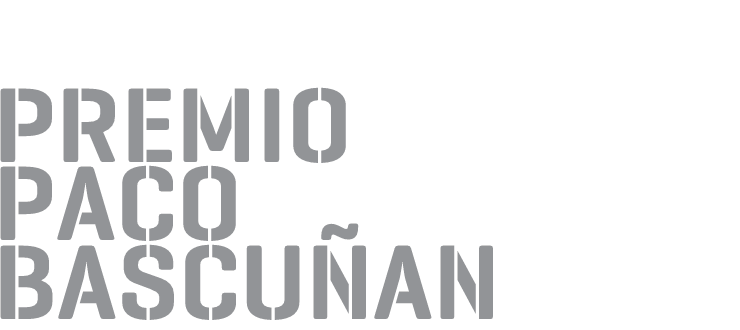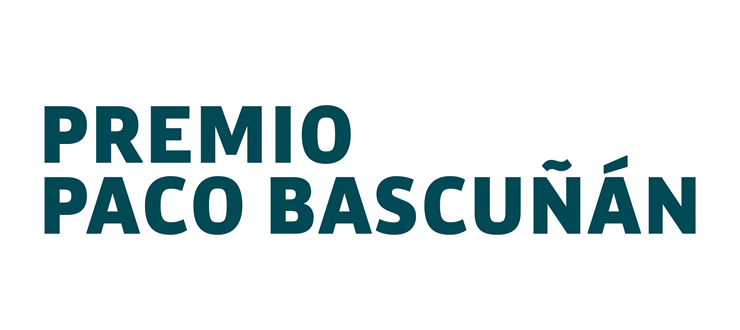
Premio de diseño de Tipografía “Paco Bascuñán”
Paco Bascuñán fue un diseñador socialmente comprometido y una de las figuras claves del diseño español desde la transición democrática hasta su muerte, acontecida prematuramente en 2009.
Convencido de que el diseño transmite valores y de que hay que otorgarle el lugar que le corresponde en la mejora de la sociedad, Bascuñán llevó también su compromiso a la mejora de la profesión.
Respetado por sus colegas de generación y admirado por los más jóvenes tanto por la calidad de su diseño como por su coherencia vital y su apertura de miras, Bascuñán fue y es un referente para quienes creen que el diseño es una profesión abierta y plural.
El Premio Paco Bascuñán es un homenaje a su figura pero, sobre todo, es la continuación de su labor en apoyo a los más jóvenes.
Bases de la convocatoria 2012
Presentación
El premio de tipografía Paco Bascuñán se plantea con dos objetivos principales: fomentar la tipografía y el diseño de tipos entre las nuevas generaciones y ser, a su vez, un homenaje a la figura de Paco Bascuñán, diseñador y tipógrafo, que siempre supo apoyar a los más jóvenes.
Bases de participación
La participación es gratuita. No podrán presentarse más de dos trabajos por autor. Podrán participar todos aquellos jóvenes menores de 25 años (cumplidos antes de Julio de 2012) con nacionalidad Española o residentes en territorio Español. Será necesaria la presentación de dicha documentación (copia de DNI o tarjeta de residencia) conjuntamente con los datos del autor.
Los trabajos presentados deberán haber sido realizados por su autor entre Enero de 2010 y Mayo de 2012.
Categorías
Se admiten alfabetos compuestos por glifos pertenecientes a cualquiera de los sistemas de escritura existentes conocidos.
1. Texto: alfabetos de estilo único o con múltiples variantes estilísticas diseñados básicamente para su uso en la composición de texto.
2. Display: alfabetos de estilo único o con múltiples variantes estilísticas diseñados para su uso a gran tamaño.
3. Ornamentales: conjuntos compuestos por glifos cuyo uso esté previsto para aplicaciones especiales: signos matemáticos, signos fonéticos, iconos, pictogramas, viñetas, ornamentos y todos aquellos casos no incluidos en las categorías anteriores.
Los alfabetos presentados no necesariamente deberán existir como fuentes digitales, aunque sí deberán estar completos.
Temas
Los trabajos presentados deberán ser originales, aunque pueda tratarse de interpretaciones o «revivals» tipográficos. En este caso se deberá notificar y explicitar dichos referentes. No serán aceptadas las digitalizaciones o trabajos derivados de tipografías ya existentes.
Jurado
Formado por algunos de los conferenciantes invitados al congreso, así como de miembros de la ADCV. Los miembros del jurado son: Dave Crossland, Gerard Unger, Gustavo Ferreira, Christian Annyas y Dylan Kendle.
La lista completa de miembros del jurado se hará pública en breve.
Premio
El premio será único (independientemente de la categoría), aunque el jurado pueda contemplar, a su juicio, algún título de carácter honorífico.
Dicho premio consiste en cubrir los gastos de inscripción para la asistencia a un Congreso de Tipografía internacional, incluidos los gastos de viaje y manutención (establecidos según criterio de ADCV) para una persona.
Durante el Congreso se hará la entrega oficial del premio y de un trofeo al ganador. El trofeo ha sido especialmente diseñado por Dani Nebot.
Criterios
Se valorará la calidad del material presentado. Se respetarán las decisiones del jurado. El premio podrá ser declarado desierto.
Presentación de trabajos
Los trabajos deberán ser presentados impresos en formato A3 vertical (420mm x 297mm), en blanco y negro (calidad mínima de 600 dpi), montados en soporte rígido (sin márgenes). Cada tipografía se mostrará impresa en un máximo de dos plafones o piezas y hasta un máximo de tres plafones si se trata de una familia tipográfica, independientemente de la cantidad de variantes estilísticas que pueda contener.
El diseño de cada pieza es libre. Las piezas pueden presentar las tipografías aplicadas en títulos o en composiciones de texto de cualquier tipo. Será imprescindible mostrar todos los caracteres básicos contenidos en la fuente (caja alta, caja baja, numerales y signos básicos)*. Es recomendable, aunque no obligatorio, mostrar aquellos glifos que se consideren importantes y que completen la fuente.
Es responsabilidad del concursante que el material llegue en perfectas condiciones para poder ser evaluado correctamente por el jurado.
En el margen inferior izquierdo deberá aparecer (en cuerpo 12) el nombre de la fuente, así como la fecha de realización. En caso de tratarse de un «revival» deberá explicitarse el nombre del referente principal. No podrá aparecer el nombre del autor en ningún caso.
El nombre del autor, así como sus datos personales, deberá estar contenido dentro de un sobre cerrado (con copia de su DNI o tarjeta de residencia) y pegado detrás del soporte de cada pieza. En el anverso del sobre deberá únicamente aparecer el nombre de la tipografía como referencia y para evitar confusión.
Mireia Gordi, ganadora de la primera edición del Premio Paco Bacuñán con su tipografía Gorgonzola, y Albert Trulls Muntañá, premiado con un accesit por la tipo Reid.
Gorgonzola es la tipografía de inspiración caligráfica y con un estilo fresco y agradable (en palabras del jurado) que ganó el Primer Premio Paco Bascuñán en el año 2010.